38节有了这几款字体
又到了给我们女同胞么放半天假的节日了,葱花心里开森无比,还能收到公司送来的娇艳欲滴的玫瑰,要知道平时男票都很少给买,捂脸捂脸。下面就推荐给大家几款38节常用的一些中文字体,助力各位女仙儿们早点完工去过节。
推荐字体前,先说说38节活动的思路,38节现在都改叫女王节、女神节、女生节了,主要叫38节太难听,一些购物网站为了让女同胞们更痛快的把口袋里的钱都掏出来,各种的名词追捧。天猫平台的标志性女神节logo早早就挂在了最显眼的地方,所以主要看你的产品定位是偏向哪一种,是霸气十足的女王or自信慢慢的女神or元气满满的女生,从这几方面入手,葱花把字体分好类推荐给大家。
女王级
关键词:霸气
1、阿里智能黑
这款字体是阿里和汉仪结合人工智能设计出的一款字体,字体坚毅有力,粗细对比强烈,是做电商广告标题常用的字体。最让我们钟爱它的原因就是针对阿里平台可免费商用。
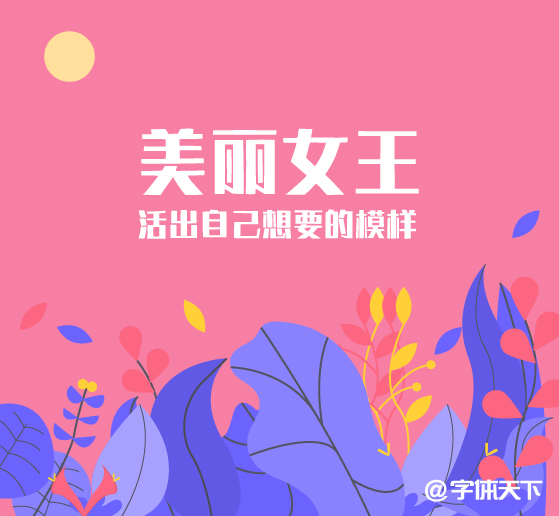
2、汉仪铸字超然体
相比阿里智能黑,这款字体具有更多的设计细节。比如下面的“丽”字横向笔画与竖向笔画之间没有填实,做了留空,让字体看起来更加透气。
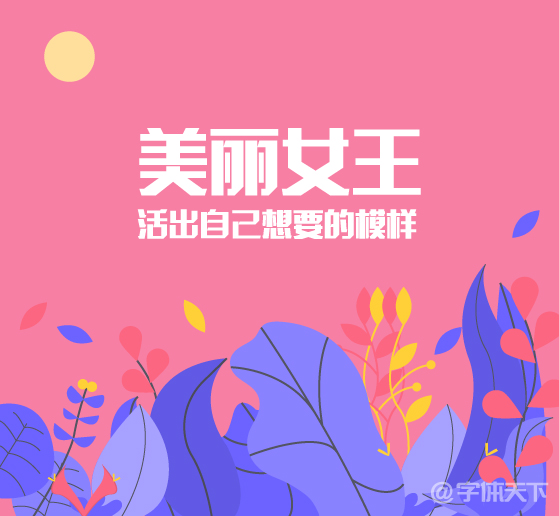
3、锐字工房光芒黑简
相比上面两款字体,这款字体形体比较矮短,横竖笔画粗细对比更加强烈,也常用于广告设计的使用。
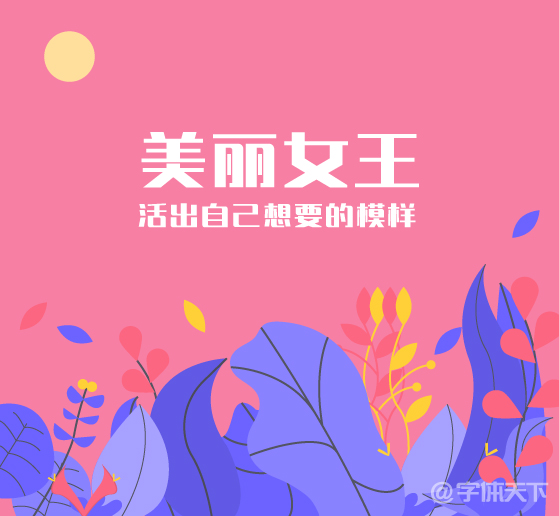
女神级
关键词:精致、优雅、自信
1、造字工房尚雅
这款字体结合了宋体的笔画特征,去繁存简,横竖笔画粗细对比强烈,整体厚重不失柔美,更加时尚大气。
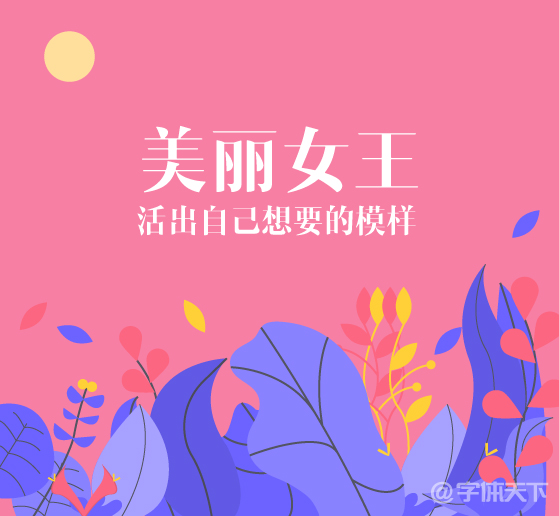
2、造字工房朗倩
字体粗细均匀,笔画流畅。
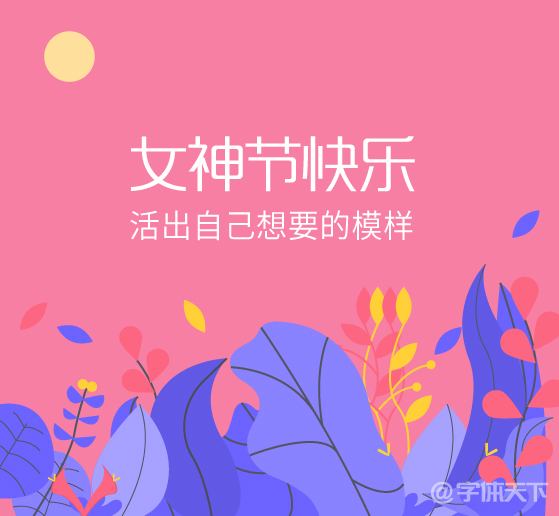
3、造字工房思研
字体笔画比较偏粗,作为标题最合适了,敦厚中又不失活泼。
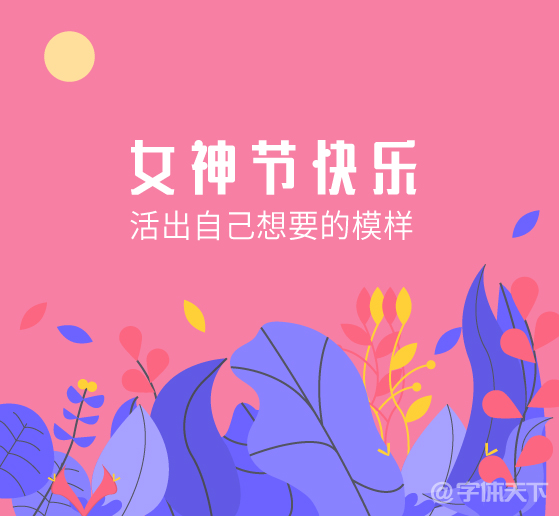
4、造字工房羽逸
笔画灵活欢快,看起来非常让人愉悦。用在节日广告上非常适合。
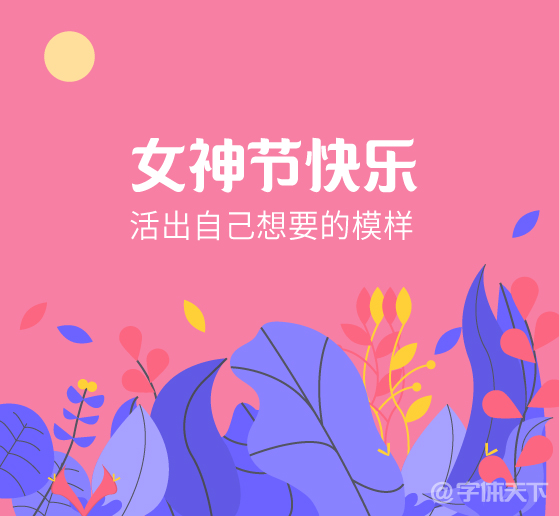
女生
关键词:青春、纯洁
1、汉仪李李体
这款字体前面的文章也介绍过,是一位画漫画的菇凉手写的字体,字体比较可爱。
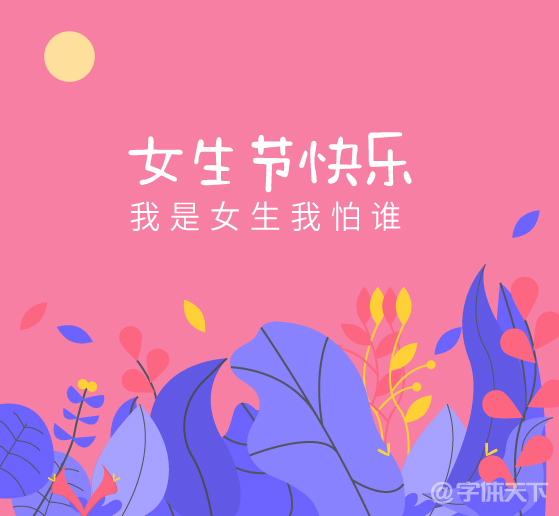
2、汉仪甜心体
这款字体是一位手工艺人亚蓝的手写体,字体可爱又欢快,在厚厚的笔画上还有小小的装饰,增添了设计感。
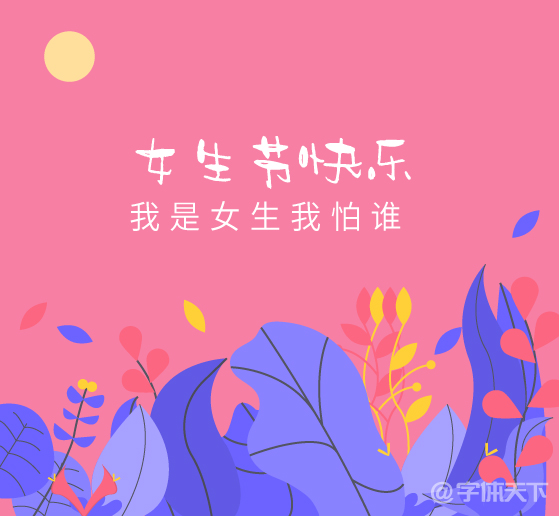
3、锐字温帅可爱
这款字体具有像面包似的的笔触,粗细对比强烈,并具有强烈的透视感,可爱又敦厚,是葱花最喜爱的卡通字体之一。
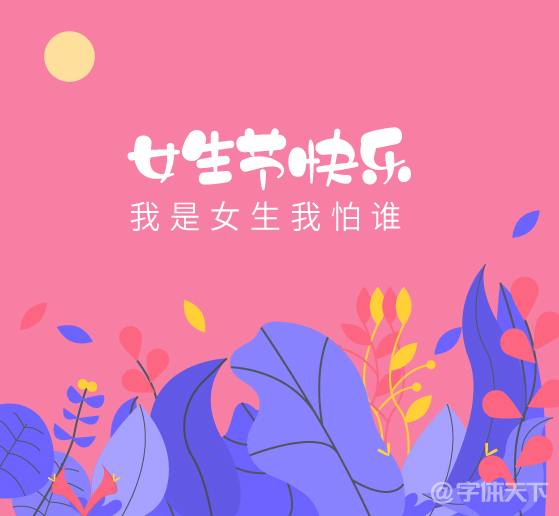
4、腾祥智黑简-W2
5、潮字社时光简